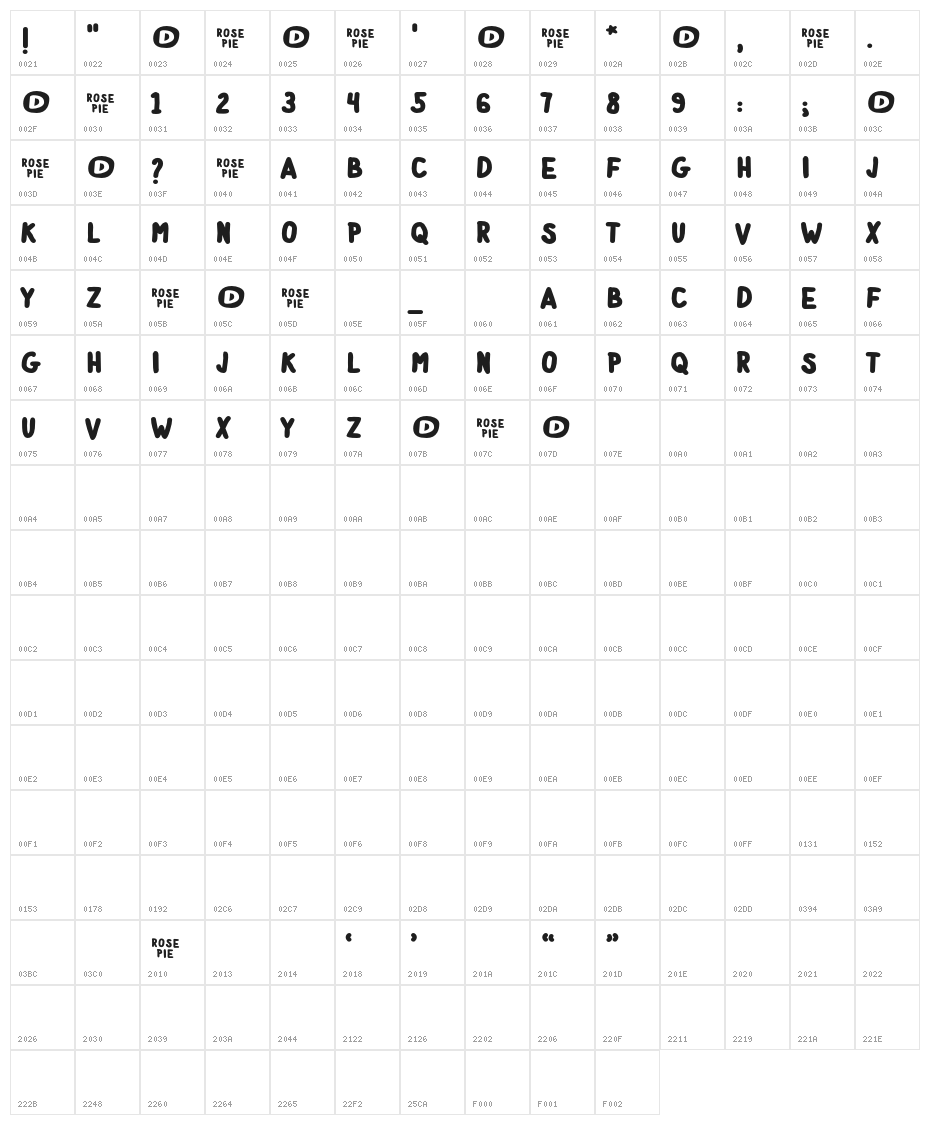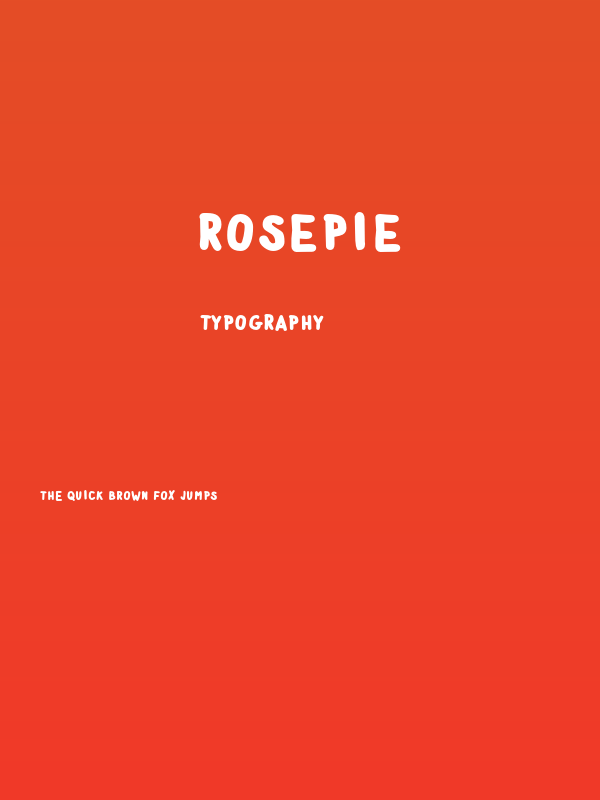
RosePie Font
| Stile generale | Playful, Whimsical |
| Progetti proposti | Ideal for children's books, comic strips, playful branding, and casual invitations. |